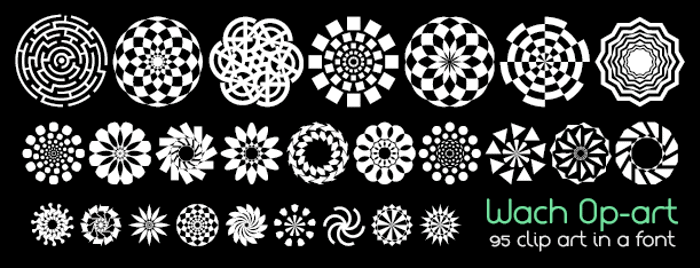
Wach Op-Art Font
ta colección de Clip art ha nacido de formas geométricas básicas y complejas moviéndose sobre el círculo, además esta inspirada en los diseños de la colección de relojes de diseño ÆØ Watches “The only one collection”, más concretamente a la serie Op-art creada por mí al final de los 80.